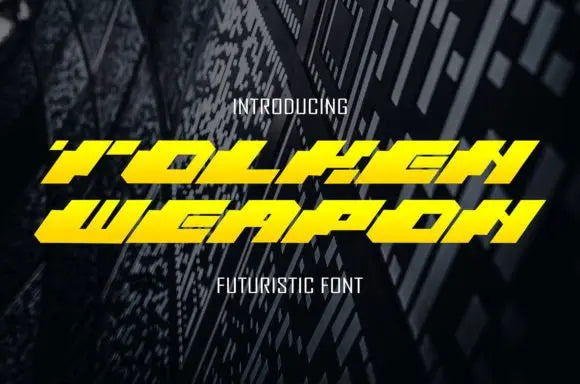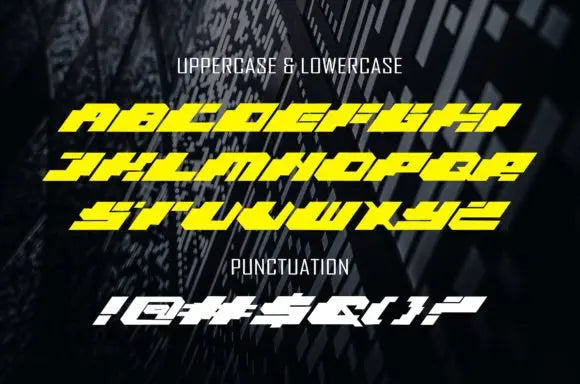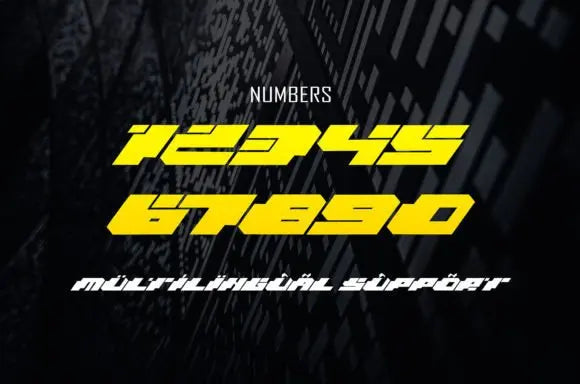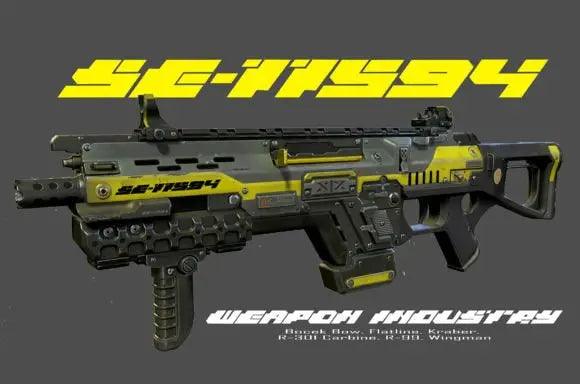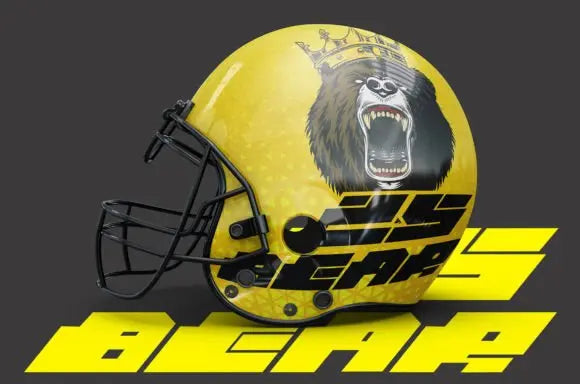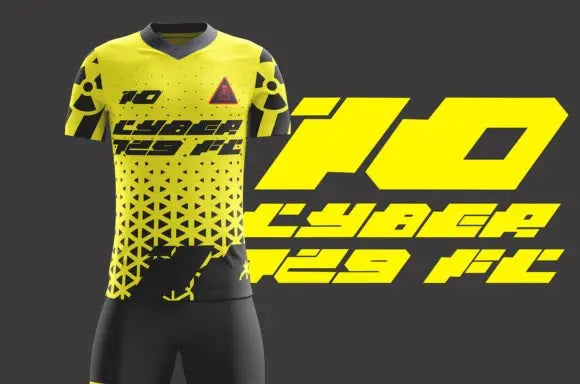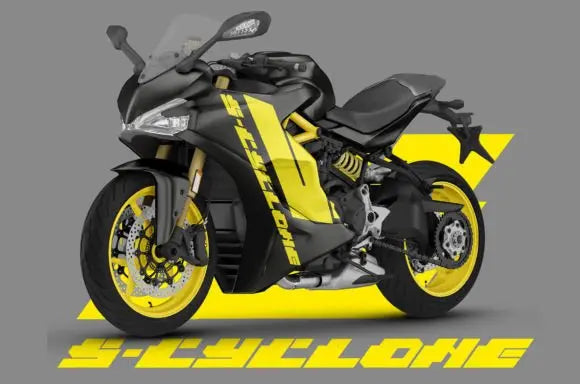
Fuente de arma Tolken
Tolken Weapon es una poderosa fuente con tema de carreras. La fuente de visualización está lista para deportes de carreras o proyectos relacionados con la automoción. Esta hermosa fuente es perfecta para titulares, camisetas, logotipos, calcomanías para automóviles, calcomanías para cascos, calcomanías, marcas, carteles, empaques, publicidad y más.
Tolken Weapon Font está diseñado para una visualización dinámica y de alta calidad. Con esta potente fuente, tus proyectos automovilísticos o de carreras seguramente se destacarán.
Perfecto para titulares, camisetas, logotipos, calcomanías para automóviles, calcomanías para cascos, calcomanías, marcas, carteles y más. Lleva tus diseños al siguiente nivel con esta fuente profesional.